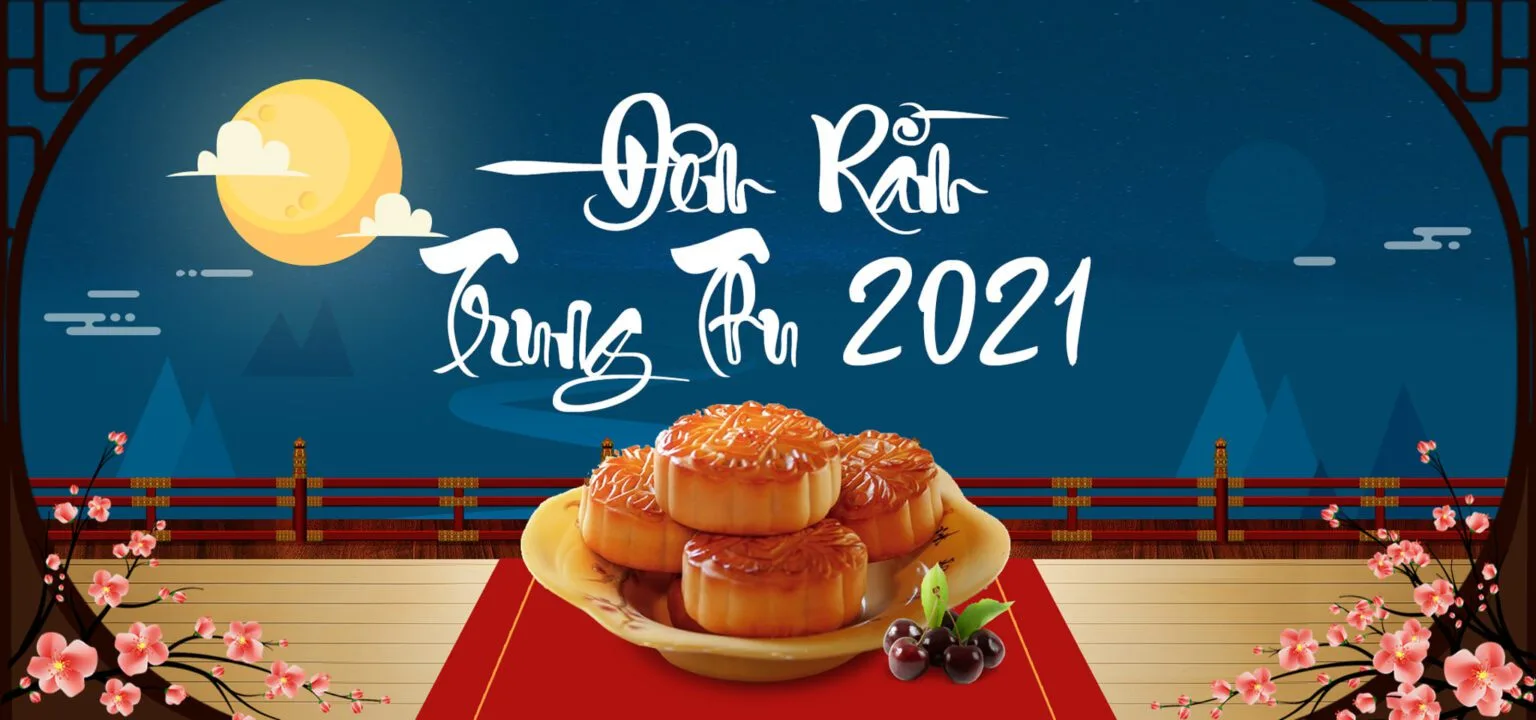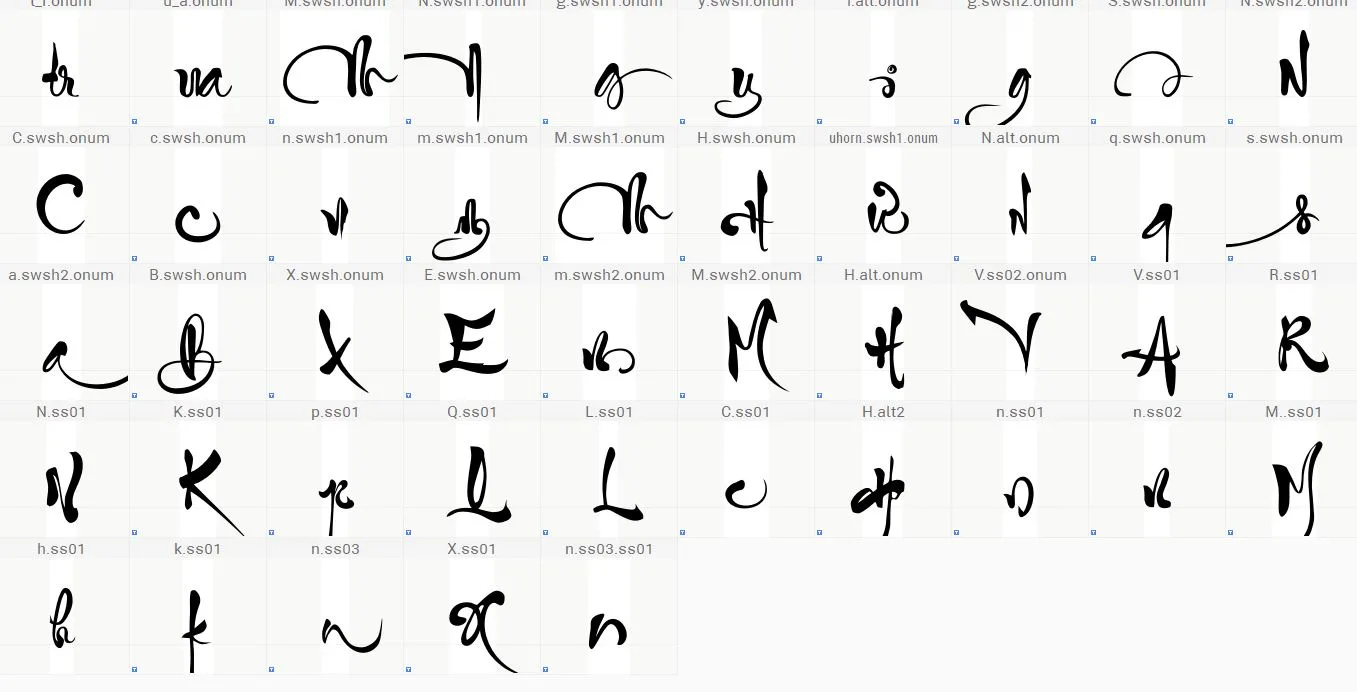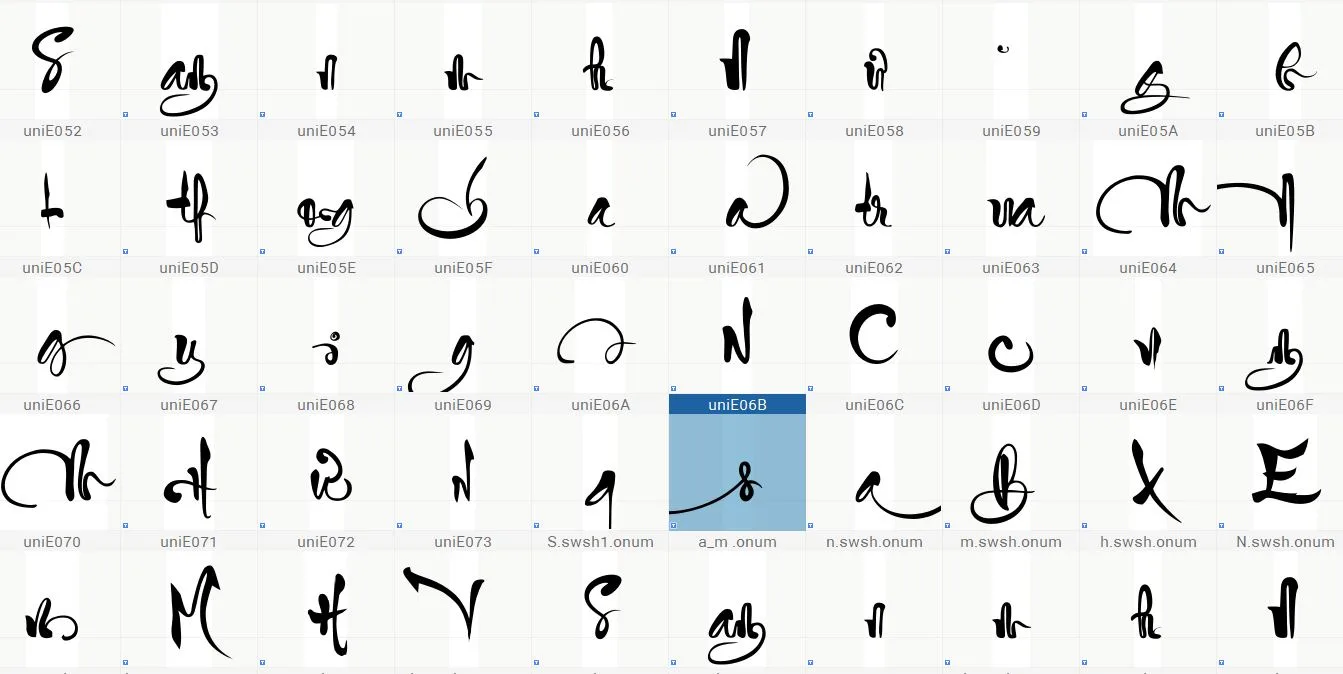
Font Thư pháp Tiểu Tự Bản full V2
Bạn đang tìm kiếm một font chữ thư pháp độc đáo để thổi hồn vào tác phẩm nghệ thuật của mình? Font Thư Pháp Tiểu Tự FontZin chính là sự lựa chọn hoàn hảo dành cho bạn!
• Được thiết kế bởi Đức Thủy, font chữ này mang đến nét đẹp thanh tao, tinh tế của thư pháp Việt Nam, đồng thời thể hiện sự sáng tạo và phong cách riêng của bạn.
• Nét chữ dựa trên chữ thư pháp viết tay bằng bút lông nhỏ, font chữ này phù hợp với các thiết kế mang đậm tính nghệ thuật và truyền thống.
Bài viết này, chúng tôi muốn giới thiệu và chia sẻ với các bạn bộ font Fz Thư Pháp Tiểu Tự Bản Full V2, một bộ font chữ thư pháp tuyệt đẹp và đầy tính ứng dụng.
Thư pháp là một nét đẹp văn hóa truyền thống của Việt Nam, ẩn chứa trong đó là sự tinh tế và tao nhã. Ngày nay, thư pháp được ứng dụng rộng rãi trong nhiều lĩnh vực khác nhau như thiết kế đồ họa, quảng cáo, thiệp mừng,…
Nhằm đáp ứng nhu cầu sử dụng font thư pháp ngày càng cao, FontZin đã cho ra mắt bộ font thư pháp Tiểu Tự. Đây là một trong những bộ font thư pháp được yêu thích nhất hiện nay bởi những ưu điểm nổi bật sau:
I. Đôi nét về Font Thư pháp Tiểu tự FontZin
Nếu bạn là người chuyên sưu tầm những font chữ việt hoá, đặc biệt là font thư pháp thì font Fz Thư pháp tiểu tự là một trong những font mà bạn cần đưa vào bộ sưu tầm của mình.
Font chữ là kết tinh từ những tinh hoa của nghệ thuật thư pháp truyền thống, thể hiện qua từng nét chữ uyển chuyển, mềm mại, đậm đà bản sắc văn hóa Việt.
Fz Thư pháp Tiểu tự ra đời và đã nhận được rất nhiều phản hồi tích cực từ cộng đồng yêu thích thư pháp cổ truyền của Việt Nam. Nó rất hữu ích cho các bạn yêu thích thư pháp, đặc biệt là người mới bắt đầu tiếp cận với thế giới nghệ thuật thư pháp.
Khám phá những nét độc đáo của font chữ này:
• Phông chữ lấy cảm hứng thiết kế từ những bức thư họa đẹ của các thư pháp gia Việt nam: Thúy Sky, Đặng Nga, Lão Trọc…
• Font thư pháp Tiểu Tự FontZin mô phỏng gần như chân thực chữ thư pháp Việt viết bằng bút lông nhỏ một cách tinh tế và đẹp mắt.
• Các ký tự chữ cái trong bộ font này được Đức Thủy thiết kế rất tỉ mỉ và chân thật, tái hiện trọn vẹn nét chữ thư pháp Tiểu tự. Điều này tạo ra một ấn tượng chân thực về nét chữ và tạo nên sự tinh tế trong việc thiết kế đồ họa.
• Font trợ đầy đủ tiếng Việt, latin, dấu, số, thanh sắc và rất nhiều kí tự mở rộng thay thế cho các chữ cái cơ bản đồng thời còn được căn chỉnh hợp lý để có thể sử dụng dễ dàng trên các phần mềm pc và các ứng dụng thiết kế trên điện thoại, máy tính bảng.
• Tính ứng dụng cao: Font chữ có thể sử dụng cho nhiều mục đích khác nhau như thiết kế thiệp chúc mừng, logo, banner, viết thư pháp nghệ thuật, trang trí nội thất, in ấn ấn phẩm,…
II. Mục đích thiết kế font chữ thư pháp Tiểu tự
Mục đích của việc thiết kế nên bộ phông chữ thư pháp này là làm đa dạng và phong phú nguồn font tiếng Việt nói chung và font thư pháp nói riêng. Hi vọng bộ font chữ này được ứng dụng rộng rãi trong lĩnh vực thiết kế, đặc biệt là những thiết kế theo phong cách xưa.
III. Tính năng phông chữ thư pháp Tiểu tự FontZin
Với việc kết hợp những nét cơ bản của con chữ lại với nhau để phỏng theo phong cách viết chữ thư pháp thì Fz Tiểu tự có những tính năng như sau:
1. Nhiều kí tự đẹp thay thế và mã hóa UPA
Bộ font tiểu tự này có đầy đủ các ký tự cần thiết để viết chữ thư pháp tiểu tự, và điều đặc biệt là bộ font còn cung cấp nhiều ký tự thay thế được mã hóa code UPA, giúp bạn có thể thiết kế được những nội dung gần giống với thư pháp.
2. Font tiểu tự được Tích hợp Opentype
Với việc tích hợp Opentype giúp bạn có thể sử dụng dễ dàng trên các phần mềm, nền tảng khác nhau. Bạn có thể sử dụng dễ dàng trên các phần mềm, nền tảng khác nhau như Adobe Illustrator, Adobe Photoshop, Microsoft Word, v.v. Bạn không cần phải lo lắng về việc cài đặt phần mềm hay điều chỉnh font để có thể sử dụng được bộ font này.
3. Kiểu chữ đẹp (ký tự khác mở rộng) dùng dễ dàng trên điện thoại
Do được mã hóa UPA và thêm vào Opentype nên bộ font này có thể dễ dàng sử dụng trên điện thoại.
Bạn có thể sử dụng dễ dàng trên điện thoại thông qua các ứng dụng như Phonto, PicsArt, v.v. và dùng GoogleDrive để copy các ký tự đẹp trong font chữ. Điều này giúp bạn có thể sử dụng font chữ này và tạo nên nhiều thiết kế đẹp mắt bằng chính điện thoại của mình.
4. Kerning đầy đủ bao gồm các bảng chữ cái kí tự thay thế
• Hỗ trợ tiếng Việt đầy đủ: Trong font các ký tự được mã hóa chuẩn Unicode nên các bạn có thể dùng các kiểu gõ thịnh hành như Vni hoặc Telex và bảng mã Unicode 8 để gõ Tiếng Việt với font này.
• Kerning 100% tiếng Việt: Bộ font tạo ra cho cộng đồng người Việt nên Đức Thủy đã kerning toàn bộ các cặp chữ tiếng Việt.
Font thư pháp là một loại Phông chữ được thiết kế dựa trên các nét viết của thư pháp. Font có nhiều phong cách khác nhau, tùy thuộc vào quốc gia và truyền thống văn hóa của từng địa phương. Ở Việt Nam, font chữ thư pháp thường có nhiều phong cách như thư pháp tiểu tự, thư pháp đại tự, v.v.
Bộ font này có thể sử dụng trên nhiều phần mềm và nền tảng khác nhau, đặc biệt là trên điện thoại, giúp người dùng dễ dàng tiếp cận với thế giới thư pháp.